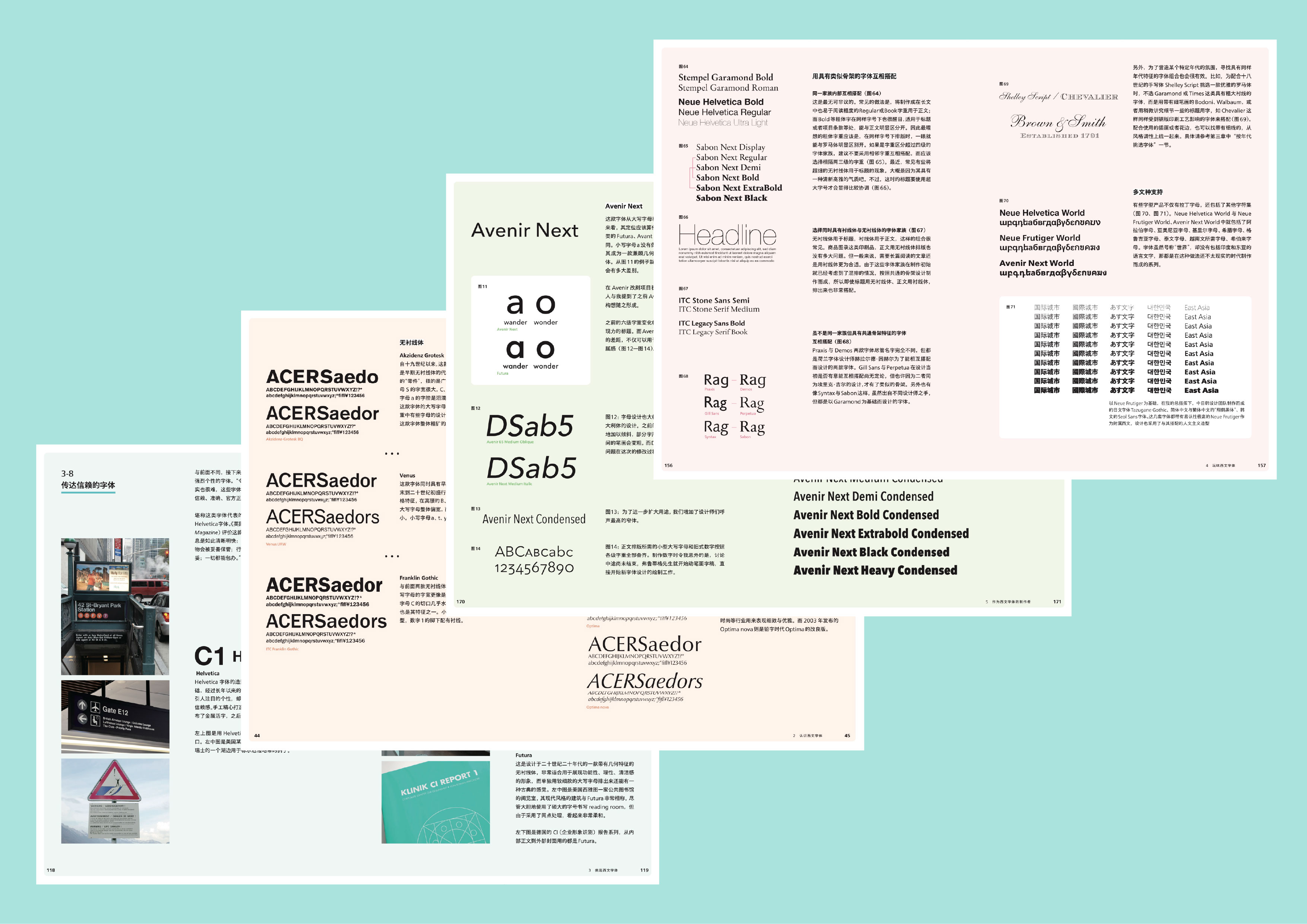
西文字体
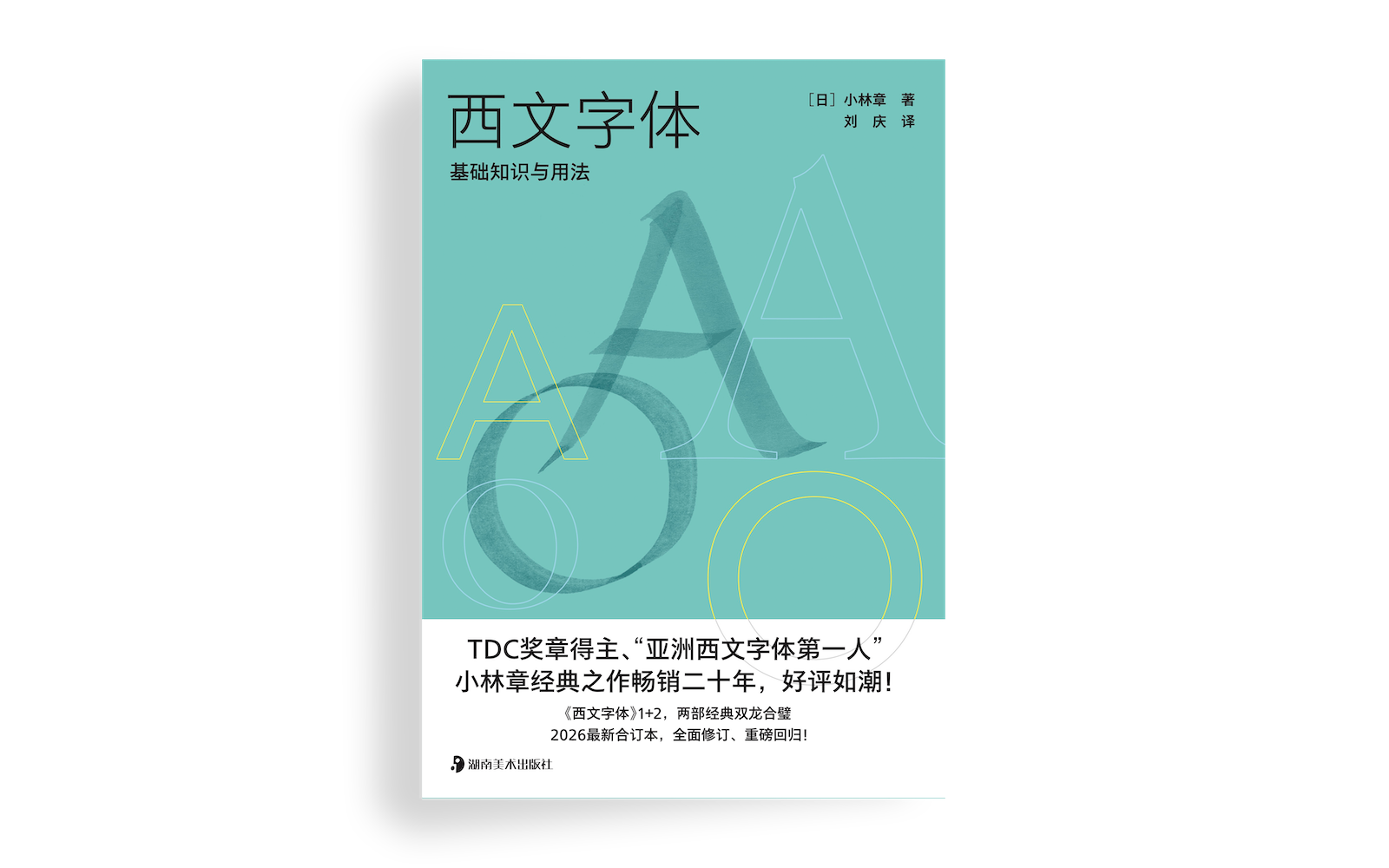
小林章(Akira Kobayashi)著,刘庆(Eric Liu)译。
被称作「亚洲西文字体第一人」的小林章先生撰写的著作一直深受读者喜爱。在日文原版出版二十年后,众人期待已久的修订版《西文字体:基础知识与用法》一书终于上市。该书以《西文字体:字体的背景知识和使用方法》(日文原版 2005 年,简体中文版 2014年)、《西文字体 2:经典款字体及其表现方法》(日文原版 2008 年,简体中文版 2015 年)(两本书的日文原版均由日本美术出版社出版,简体中文版均由中信出版社出版)为基础,经大幅度改写、重新编辑而成。而简体中文版则由 The Type 策划引进、经湖南美术出版社出版,依旧由本站编辑刘庆(Eric Q. Liu)负责翻译。
本书从西文字母的形成开始讲解,作者通过自己在英国的学习经历,打破了之前所深信的「用直尺圆规做罗马字」的认识误区。然后,作者从最基本的术语和基本款字体开始介绍,结合了避免出丑的排版规则,确保读者能够正确入门。面对种类繁多的西文字体,作者通过自己亲手在世界各地拍摄的丰富多彩的图片,讲解如何按年代、国别、氛围(高端感、信赖感)挑选字体,并详细介绍了灵活运用手写体、细致调整字距等实用技巧。本书在最后还剖析了作者作为一名西文字体设计师是如何思考,又是如何对名作精益求精的。无论是对于专业设计师,还是对字体感兴趣的一般爱好者,本书都是一本必备的教科书级别的经典著作。
本书作者小林章两度获得西文字体国际大赛大奖后于 2001 年移居德国。与著名字体设计师赫尔曼 · 察普夫、阿德里安 · 弗鲁蒂格共事,共同修改制作其著名的字体作品。2010 年之后负责亚欧各地品牌专用字体以及中日韩字体的监修。德国红点奖等世界知名设计奖的评审,并在各地发表演讲普及字体知识。其功绩获得认可,被纽约字体指导俱乐部授予 2022 年度 TDC 荣誉奖章。现任蒙纳字库字体创意总监。著有《西文字体:字体的背景知识和使用方法》、《西文字体 2:经典款字体及其表现方法》(日文原版均为日本美术出版社出版,简体中文版均为中信出版社出版)、《西文字体设计方法》(日文原版为 Book&Design 公司出版、简体中文版为上海人民美术出版社出版)等。
- 原题:欧文書体―基礎知識と使い方
- 原著:小林章(Akira Kobayashi)
- 翻译:刘庆(Eric Liu)
- 出版:湖南美术出版社
- 字体:蒙纳字库・翔鹤黑体